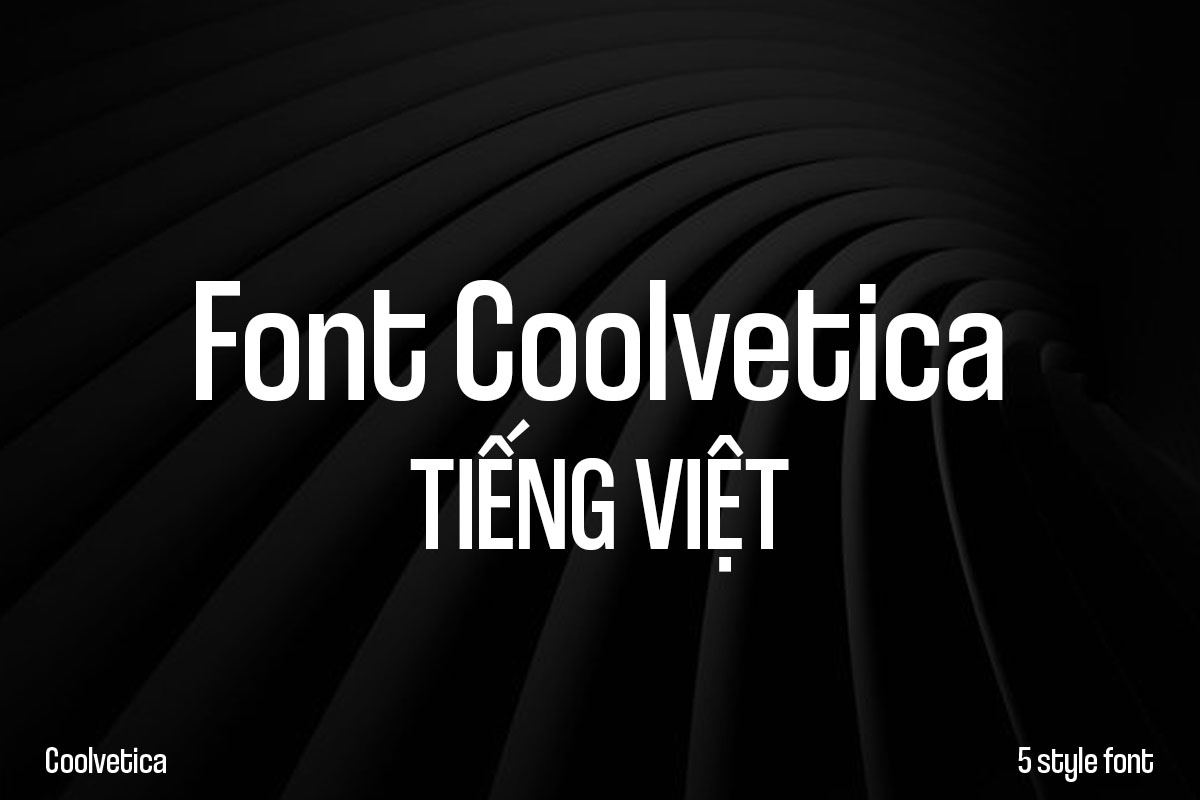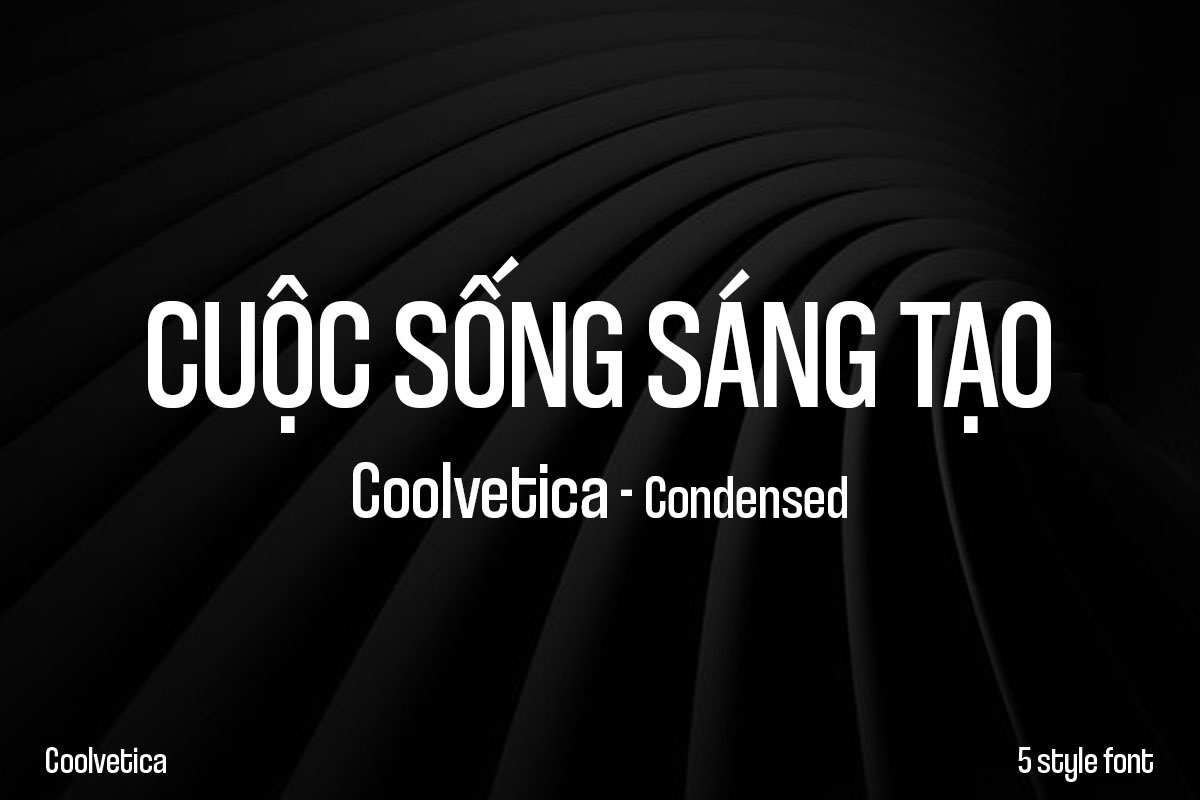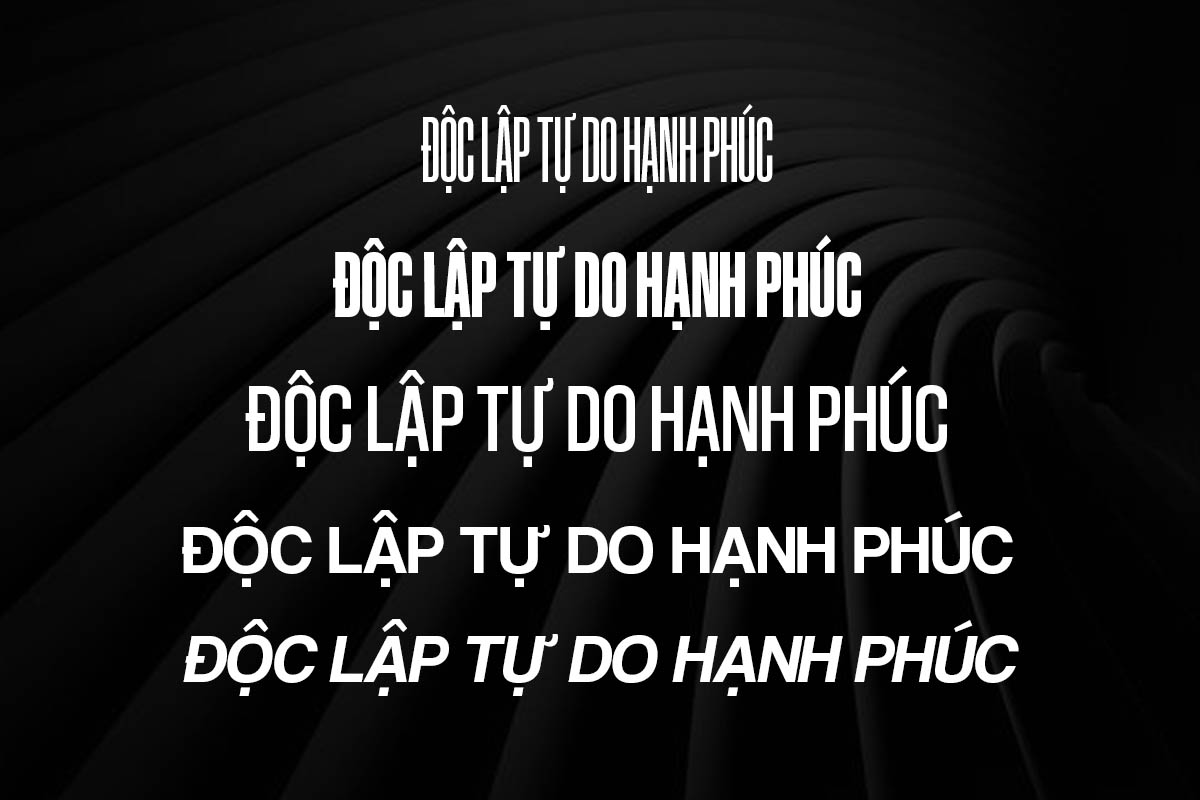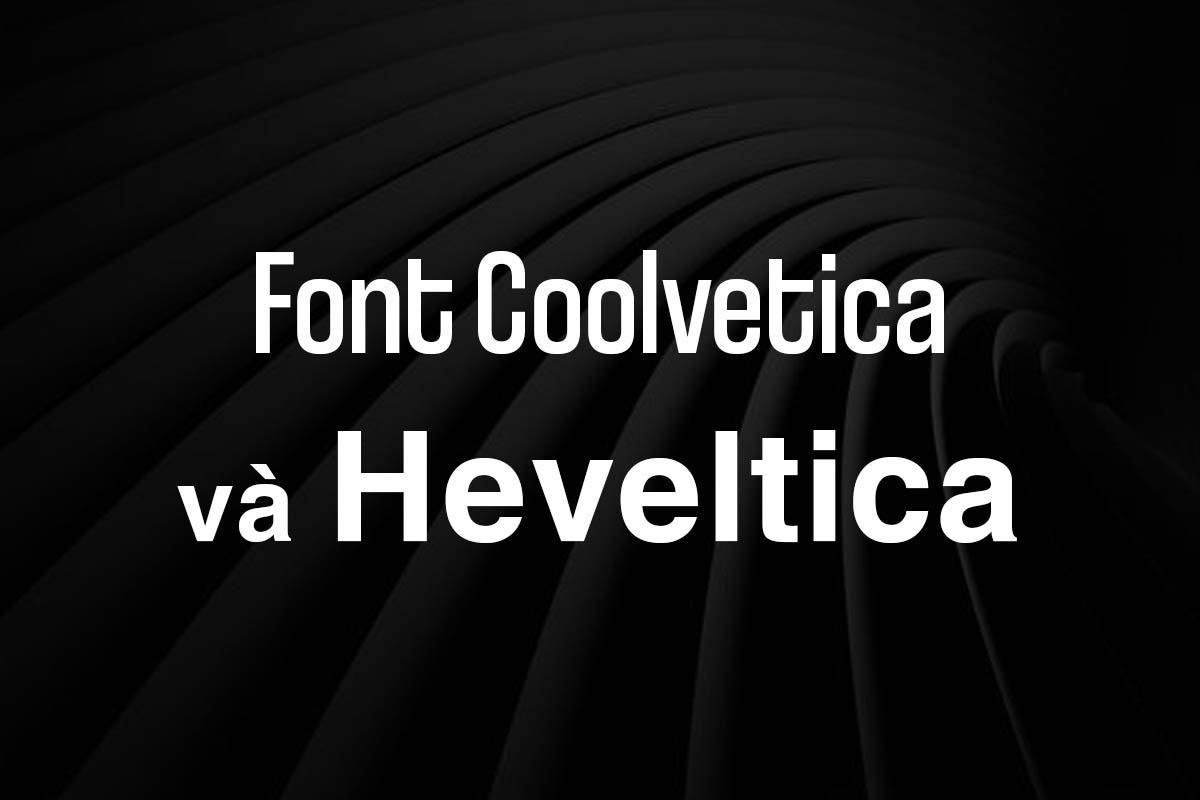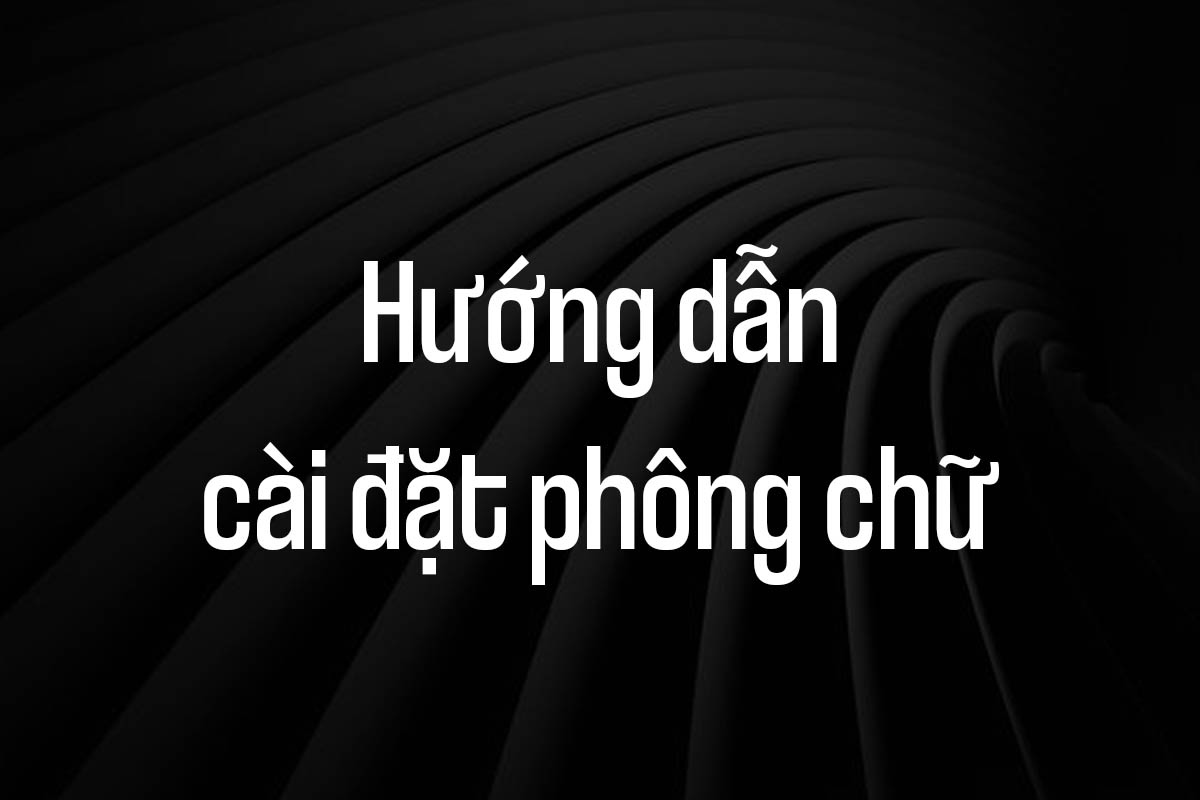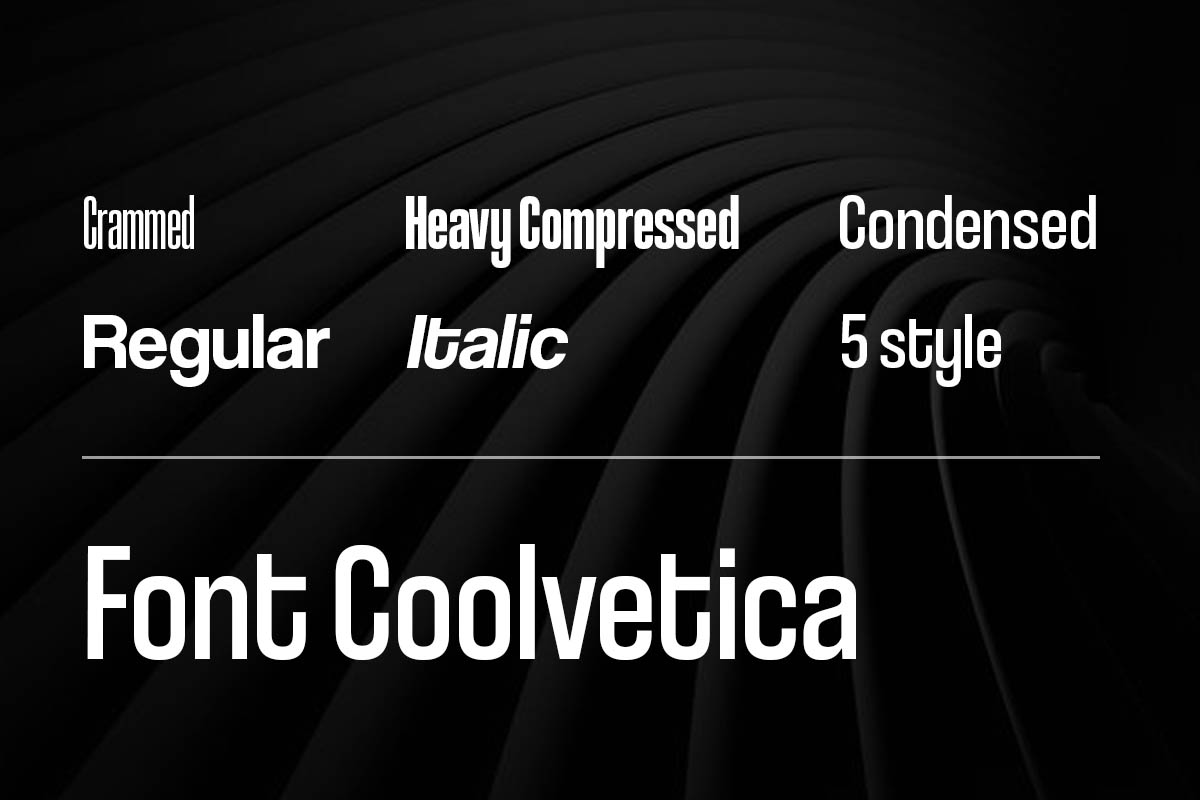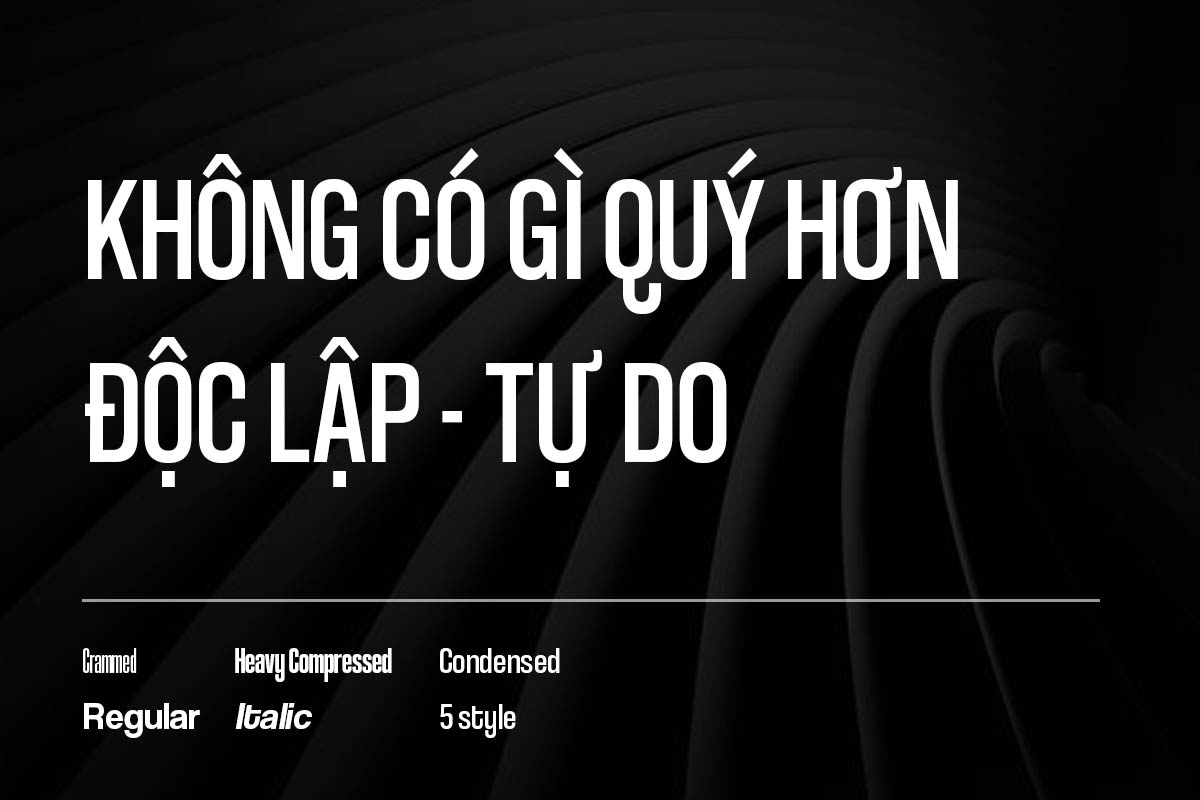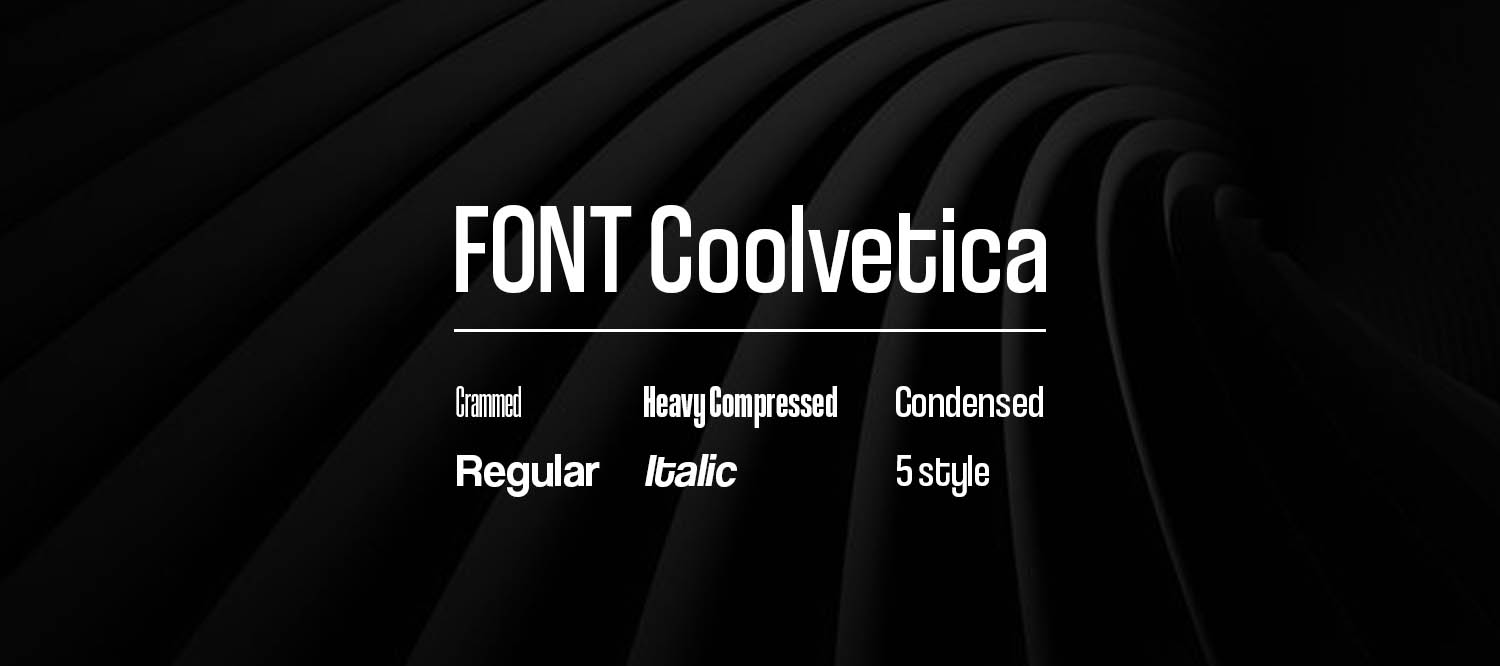
![[Tải Miễn Phí] Trọn Bộ 5 Font Chữ Coolvetica Tiếng Việt Không Chân](https://cdn.s99.vn/cloud/font-chu-tieng-viet-Coolvetica-8.jpg)
Coolvetica là một kiểu chữ sans-serif hiện đại, được thiết kế lấy cảm hứng từ phong cách quảng cáo những năm 1970 tại Mỹ. Với đường nét bo tròn, đơn giản và gọn gàng, font này mang đến sự trẻ trung, cá tính cho thiết kế. Tuy nhiên, phiên bản gốc của Coolvetica không hỗ trợ đầy đủ dấu tiếng Việt, gây trở ngại cho người dùng Việt Nam. Vì vậy, các bản Coolvetica Việt hóa ra đời nhằm lấp đầy khoảng trống này, giúp người thiết kế sử dụng font đẹp mắt này trong các dự án mang ngôn ngữ bản địa.
Coolvetica là một font chữ không chân (sans-serif), thiết kế bởi Ray Larabie – nhà sáng lập Typodermic Fonts. Nó mang lại cảm giác vừa retro vừa hiện đại, được lấy cảm hứng từ các logo doanh nghiệp thập niên 70 của Mỹ, tạo nên sự hoài cổ nhưng không lỗi thời.
Ray Larabie đã tạo ra Coolvetica như một “bản remix” của Helvetica, nhưng phá cách hơn, bo tròn và cá tính hơn. Font được chia sẻ miễn phí cho mục đích cá nhân, nhanh chóng trở nên phổ biến trong cộng đồng thiết kế quốc tế nhờ nét đặc trưng thị giác dễ nhận diện, hiện đại và phù hợp với branding trẻ trung.
Phiên bản gốc của Coolvetica không hỗ trợ các ký tự có dấu tiếng Việt như “ă”, “ê”, “ơ”, “ứ”… Điều này khiến font dù đẹp nhưng bị hạn chế khi dùng cho nội dung thuần Việt. Các bản Việt hóa giúp người dùng tận dụng tối đa thiết kế gốc, đồng thời hiển thị đầy đủ tiếng Việt có dấu trong mọi ứng dụng từ in ấn, truyền thông, đến thiết kế số.
Một trong những bản Coolvetica Việt hóa được sử dụng rộng rãi nhất hiện nay là Coolvetica Condensed Rg, thường thấy trên các website chia sẻ font như s99.vn. Đây là phiên bản giữ được gần như nguyên bản thiết kế của Coolvetica nhưng được thêm đầy đủ dấu tiếng Việt, cho phép sử dụng trọn vẹn trong thiết kế tại Việt Nam.
Bản Việt hóa này do cộng đồng designer trong nước thực hiện và chia sẻ. Tuy không rõ tên cá nhân cụ thể, nhưng quá trình Việt hóa được thực hiện cẩn thận, tuân thủ cấu trúc gốc, đảm bảo tính thẩm mỹ và đồng bộ trong các ký tự.
Coolvetica Condensed Rg hỗ trợ khoảng 90 - 95% các ký tự tiếng Việt thông dụng. Một vài tổ hợp kí tự đặc biệt có thể chưa hoàn thiện, nhưng không ảnh hưởng đến phần lớn ứng dụng thực tế, đặc biệt với thiết kế tiêu đề, poster, logo.
Coolvetica Việt hóa mang đến nhiều ưu điểm nổi bật: Thứ nhất, đây là font sans-serif nên dễ đọc, phù hợp với thiết kế số và in ấn. Thứ hai, các đường cong được bo tròn mềm mại, tạo cảm giác thân thiện, gần gũi và trẻ trung. Thứ ba, font có tính ứng dụng cao – từ thiết kế logo, tiêu đề trang web, đến bài đăng mạng xã hội hay bao bì sản phẩm.
Coolvetica và Helvetica đều là các font không chân, dễ đọc và hiện đại. Tuy nhiên, Coolvetica bo tròn nhiều hơn, tạo cảm giác mềm mại, biểu cảm và cá tính hơn so với Helvetica vốn nghiêm túc và trung tính. Nếu Helvetica thường được dùng trong tài liệu hành chính, thương hiệu cao cấp thì Coolvetica phù hợp với các thương hiệu trẻ, startup, hoặc các sản phẩm hướng đến giới trẻ.
Coolvetica Việt hóa được ứng dụng rộng rãi trong nhiều lĩnh vực thiết kế. Trong thiết kế logo, font giúp tạo ra nhận diện thương hiệu trẻ trung, thân thiện. Với poster hoặc banner sự kiện, Coolvetica dễ dàng gây ấn tượng mạnh bởi độ dày và bo cong độc đáo. Trên các nền tảng mạng xã hội như Instagram, Facebook, font tạo nên hình ảnh thương hiệu nhất quán, hiện đại. Ngoài ra, nhiều designer còn sử dụng font này cho portfolio, CV cá nhân hay tài liệu trình chiếu sáng tạo.
Coolvetica Việt hóa là lựa chọn lý tưởng cho designer chuyên nghiệp cần font sáng tạo, chủ thương hiệu nhỏ muốn nổi bật mà không cần thuê thiết kế cao cấp, và người dùng Canva/CapCut mong muốn tạo nội dung thẩm mỹ nhanh chóng. Những ai theo đuổi phong cách thiết kế trẻ, hiện đại, và năng động đều có thể tận dụng font này.
Nếu bạn đang tìm một font không chân, hiện đại, mang lại cảm giác thân thiện và cá tính, Coolvetica Việt hóa là lựa chọn đáng cân nhắc. Nó phù hợp với các dự án thiết kế trẻ trung, sáng tạo như thương hiệu startup, sản phẩm handmade, nội dung số… Tuy nhiên, nếu bạn cần sự trang trọng, truyền thống hoặc tính đồng nhất thương hiệu cao cấp, hãy cân nhắc những font khác như Helvetica, Times New Roman hoặc Charter.
Font Coolvetica Việt hóa là gì?
Là phiên bản hỗ trợ tiếng Việt của font Coolvetica, một kiểu chữ sans-serif bo tròn, hiện đại.
Coolvetica bo tròn hơn, biểu cảm hơn và thích hợp với thiết kế sáng tạo. Arial nghiêm túc, dễ đọc và phổ biến trong văn bản hành chính.